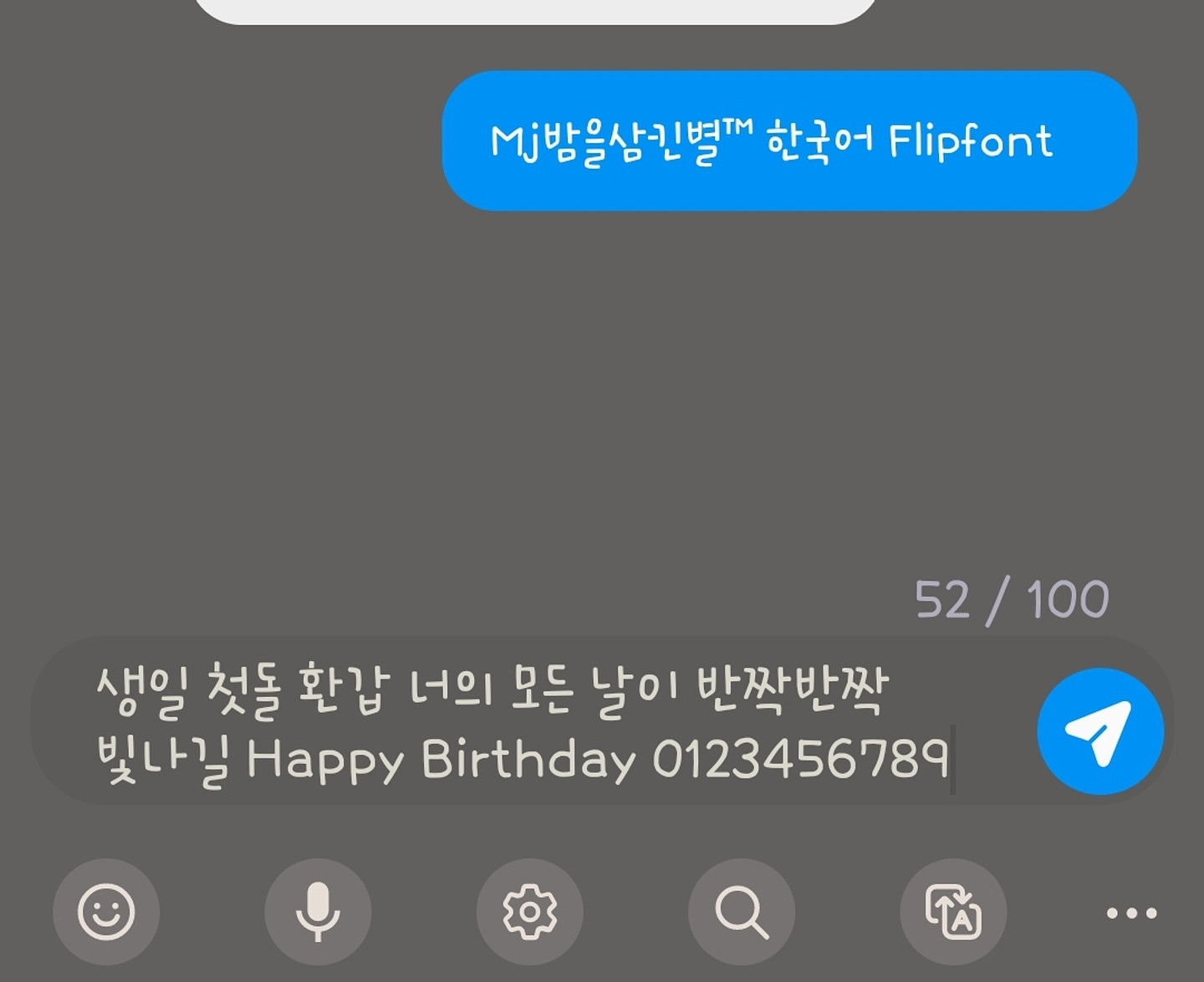
Mj밤을삼킨별
이 폰트 HU하늘고딕 140로 알려주셨는데 느낌은 비슷하지만 히읗이 다르고 사진 속 폰트가 획이 더 긴 느낌이라 정확히 알려주실분 ㅜㅜ
Mj밤을삼킨별
이 폰트 HU하늘고딕 140로 알려주셨는데 느낌은 비슷하지만 히읗이 다르고 사진 속 폰트가 획이 더 긴 느낌이라 정확히 알려주실분 ㅜㅜ